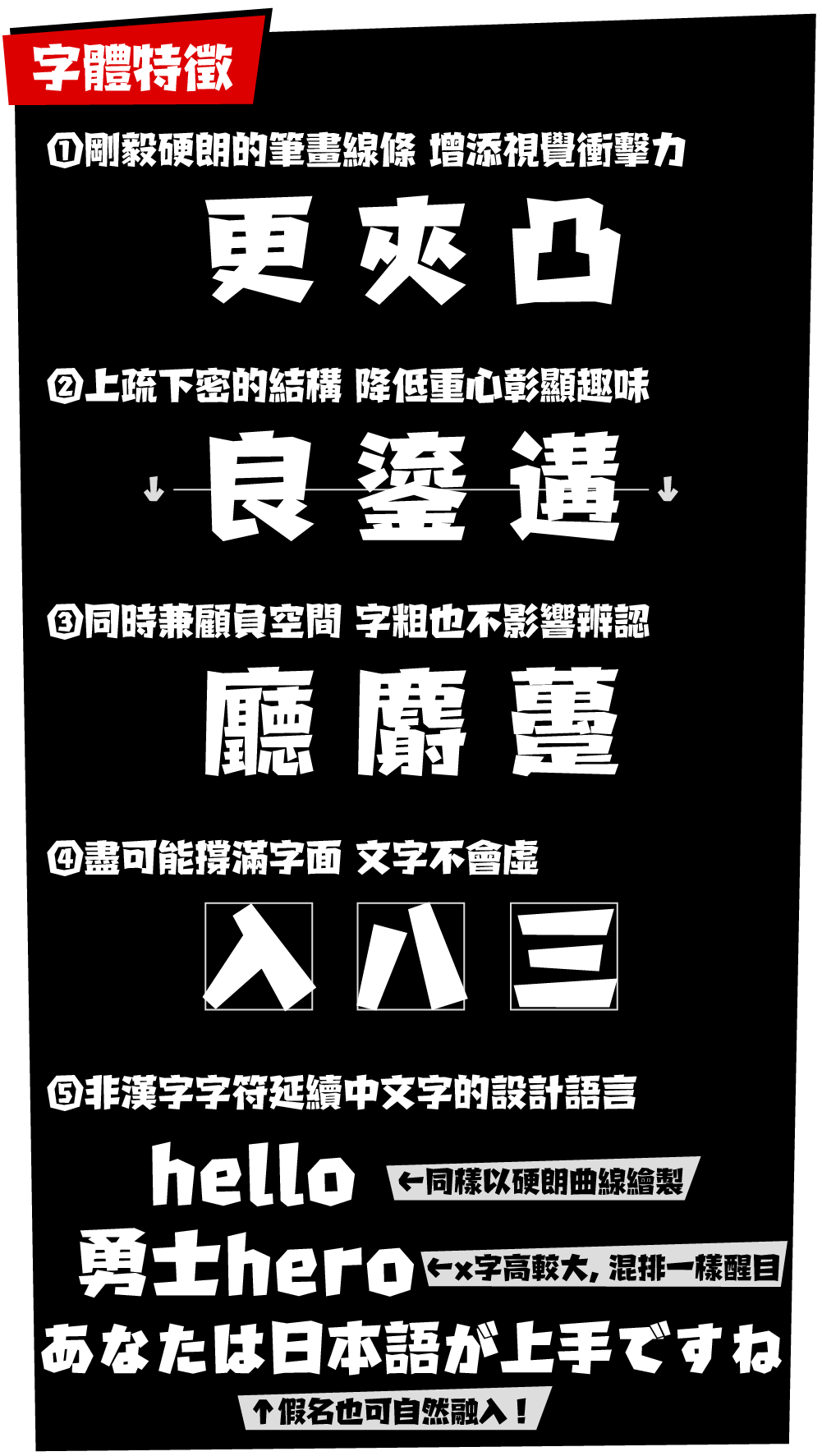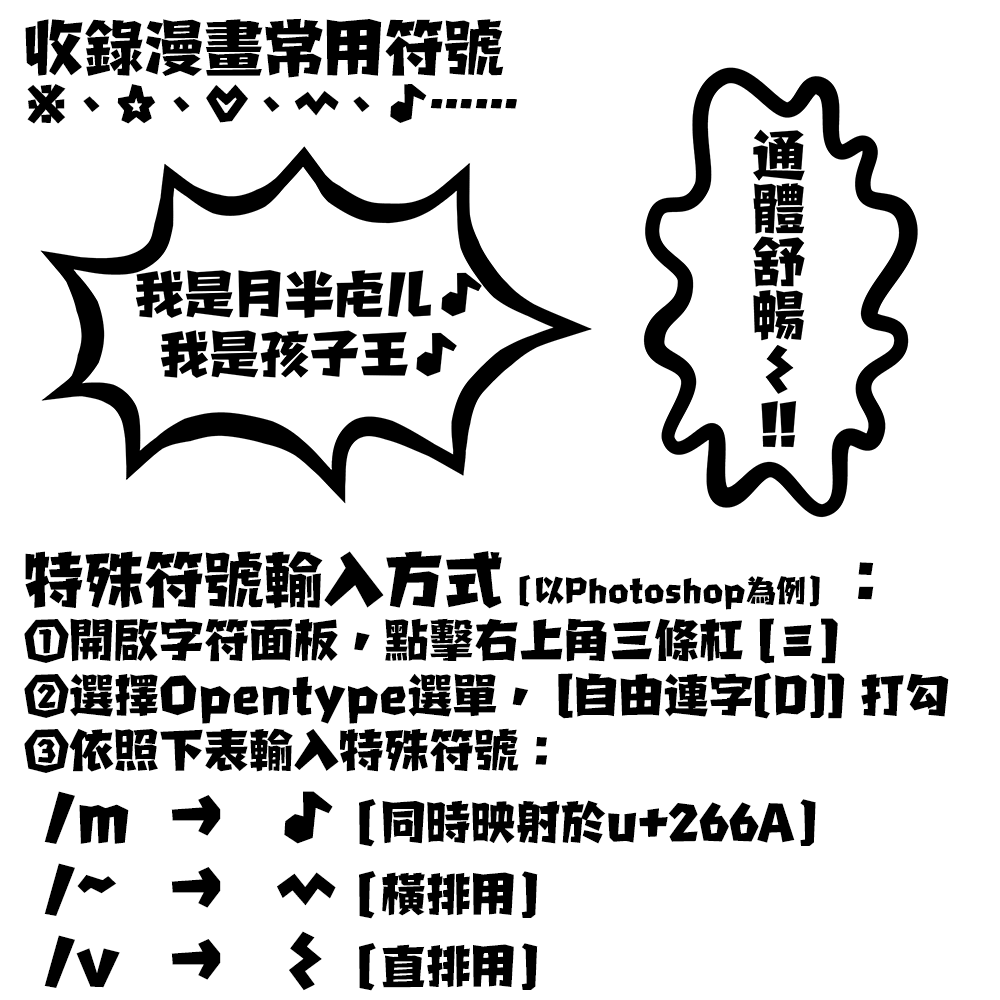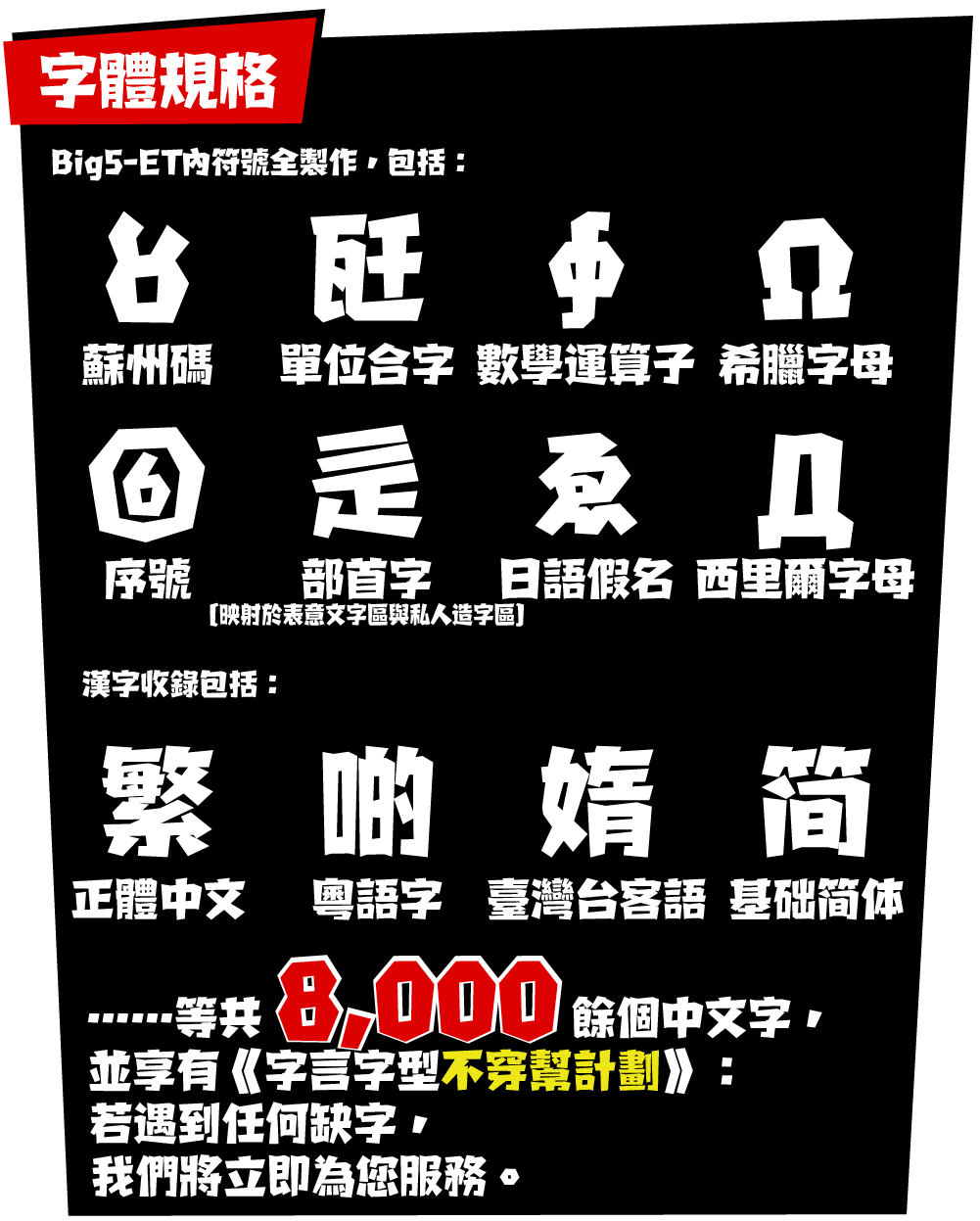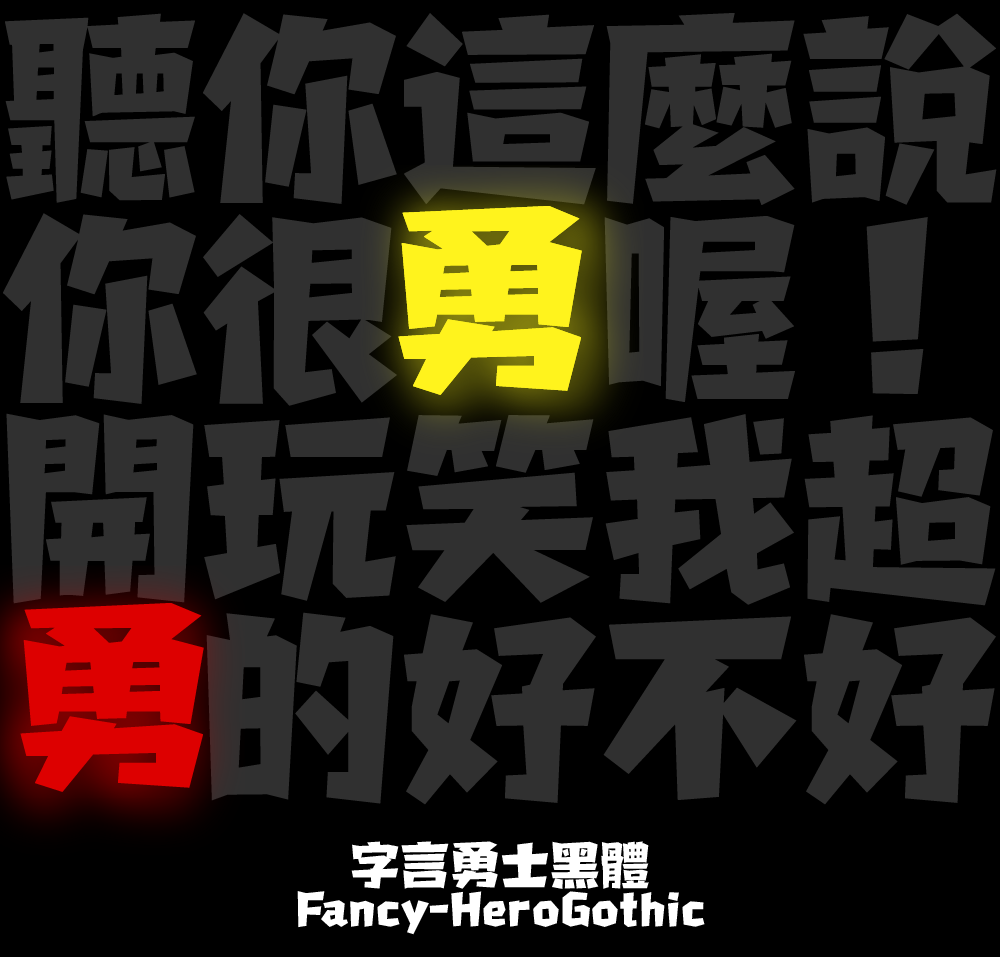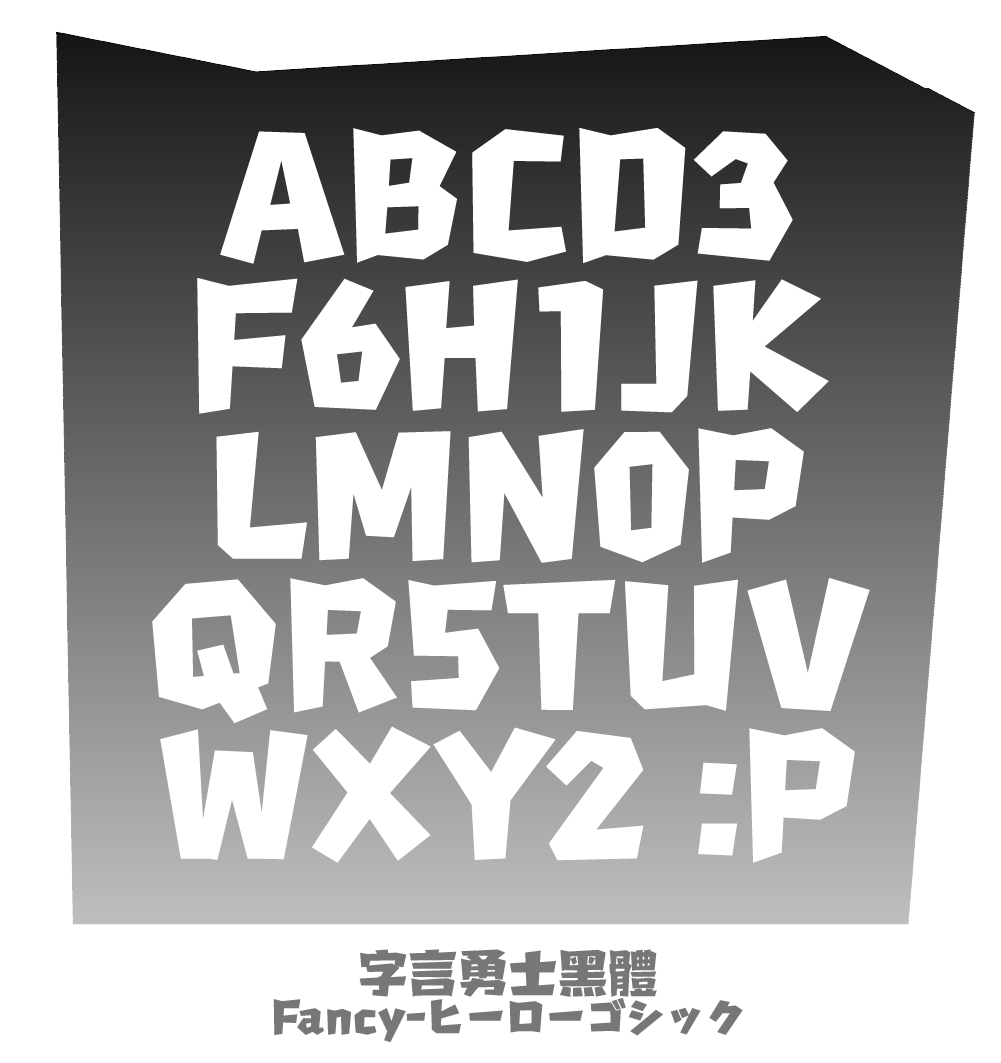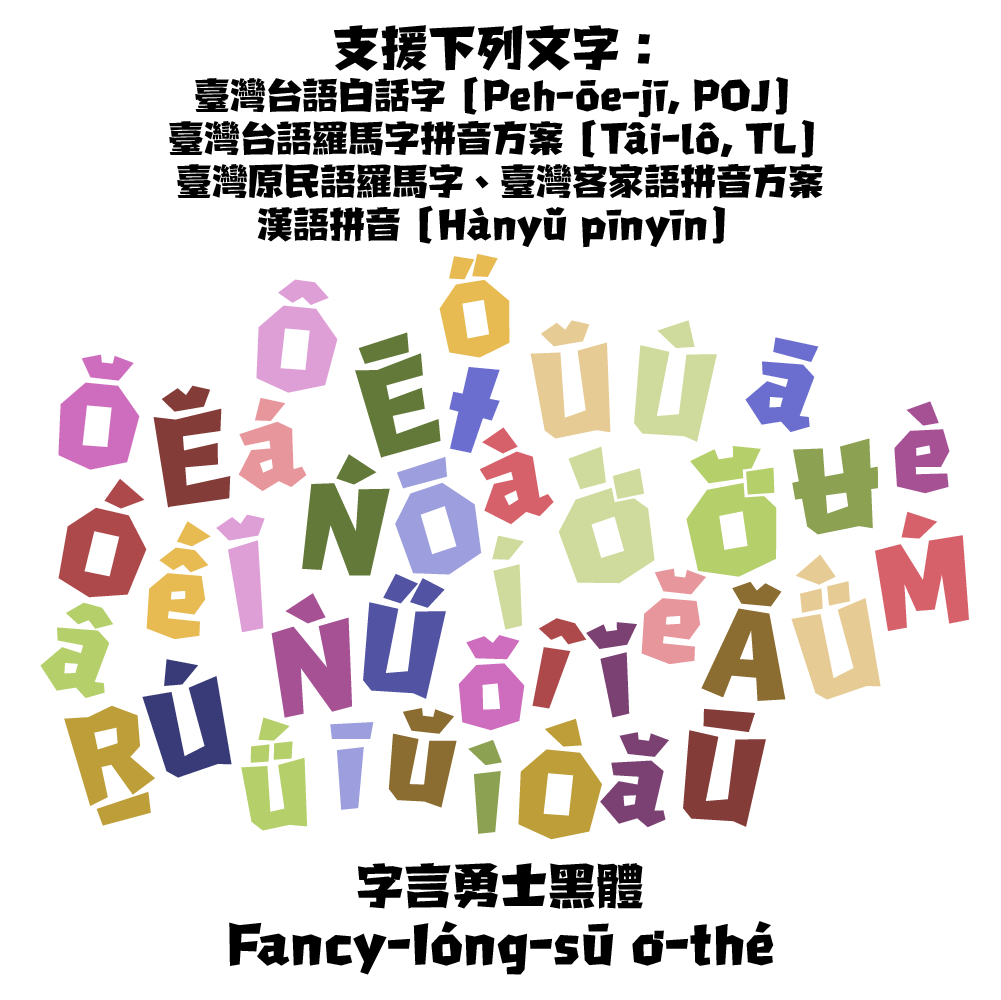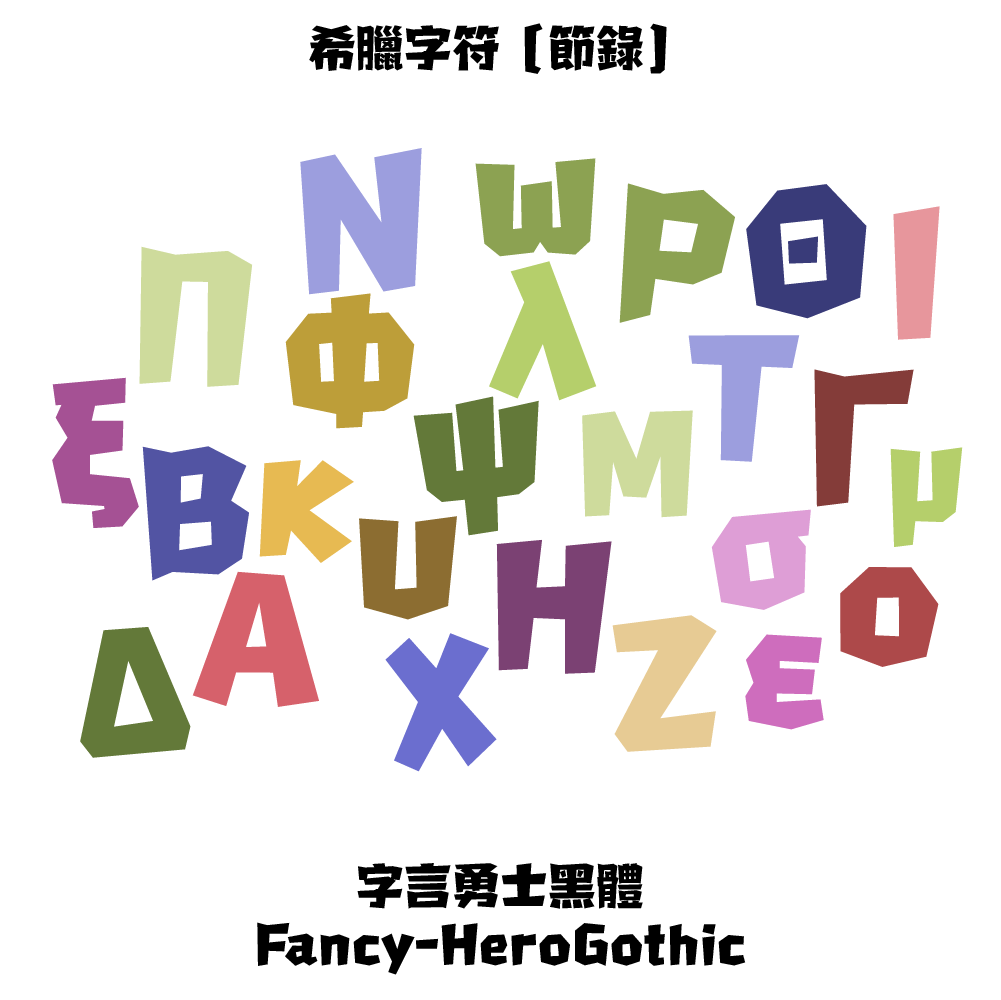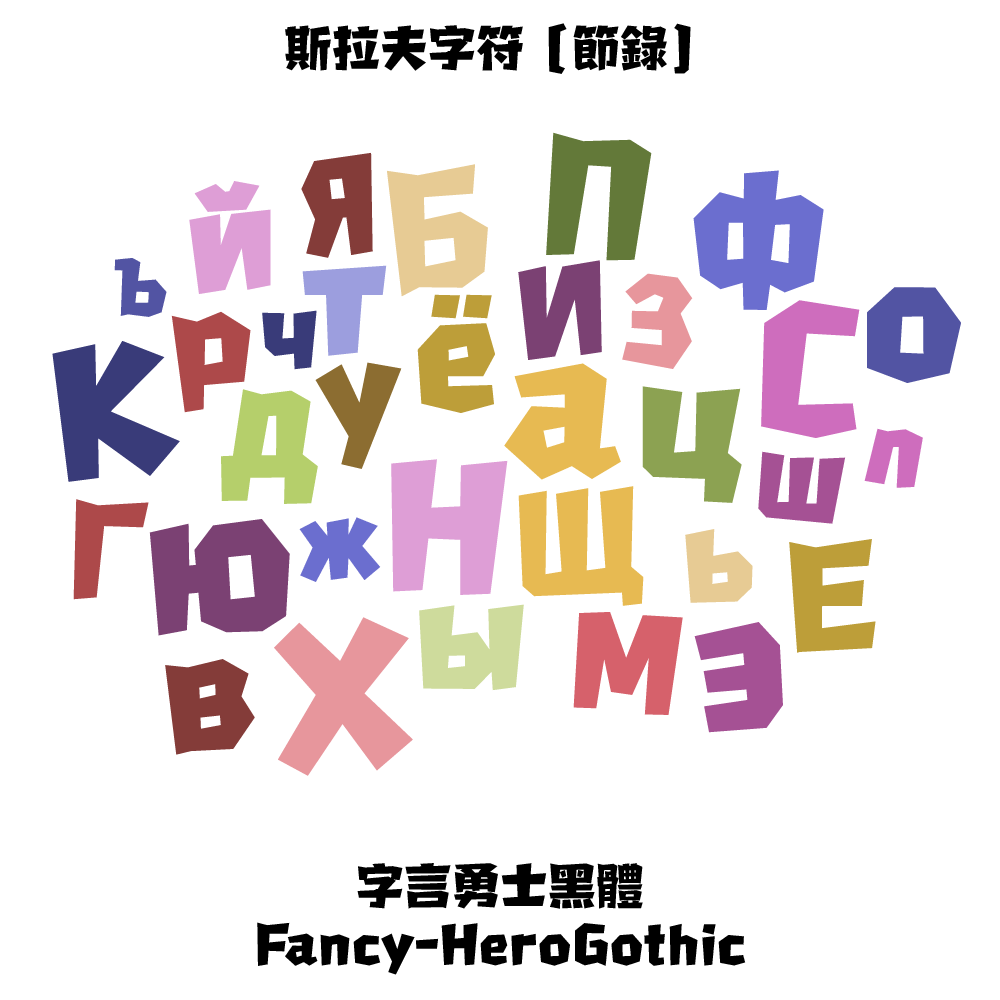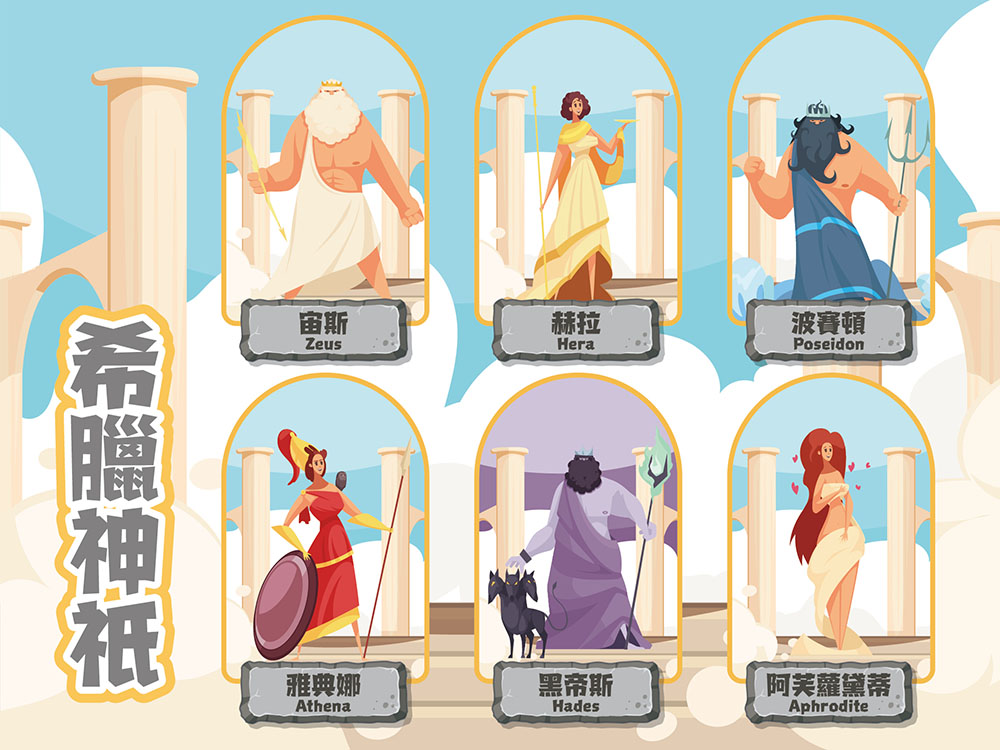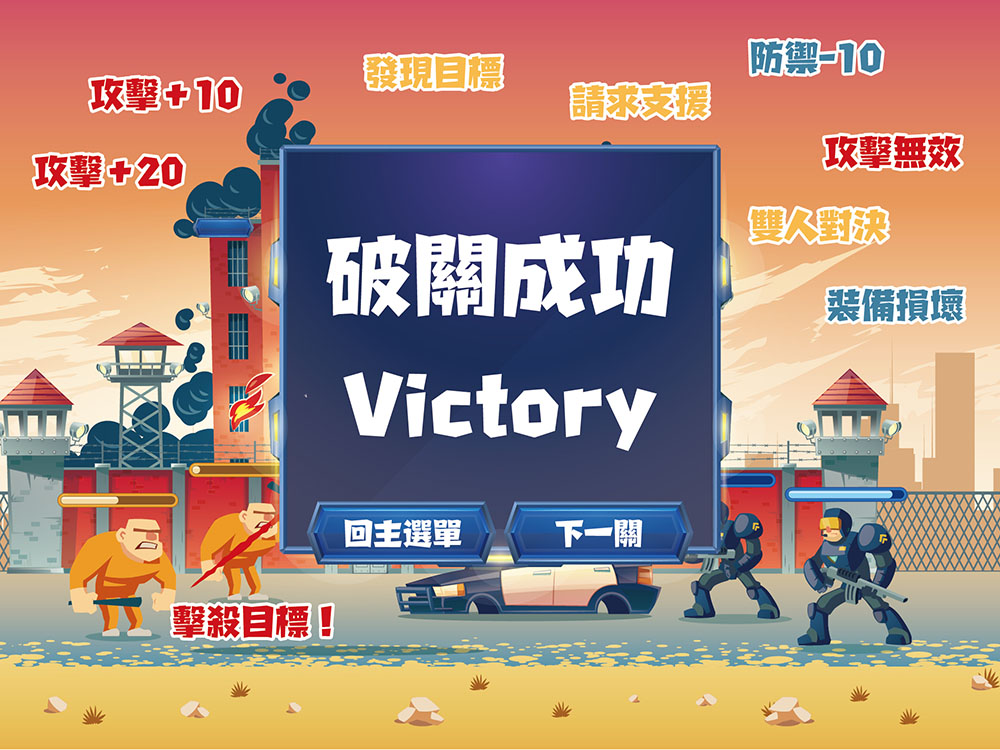
字言勇士黑體現在大約有9820字,包括歐文、數字、常用符號、8761個常用繁體字、臺客閩粵語常用字及常用簡體字,並支援臺灣台語白話字、羅馬字拼音方案(POJ, TL)、臺灣原民語羅馬字、臺灣客家語拼音方案、漢語拼音(Hànyǔ pīnyīn),另補齊了位於基本區的214個部首,亦與HKSCS及Big5-Eten中映射於ISO 10646私人造字區(PUA)的25個部首兼容。
字言勇士黑體 – 穩重清晰的粗裝飾字
作者很喜歡粗粗的字體,越粗越好。在觀察了市面上大量的粗體字,並結合自身用字經驗,創造出了這套《勇士黑體》。這套字特別注重【易讀性】,並且在設計時只使用直線條,來營造乾脆利落感。
既然這款字體的定位在於【扎實、穩重、筆畫清晰、不失識別度】,用於大標題、醒目字卡、搶眼海報是再適合不過了。